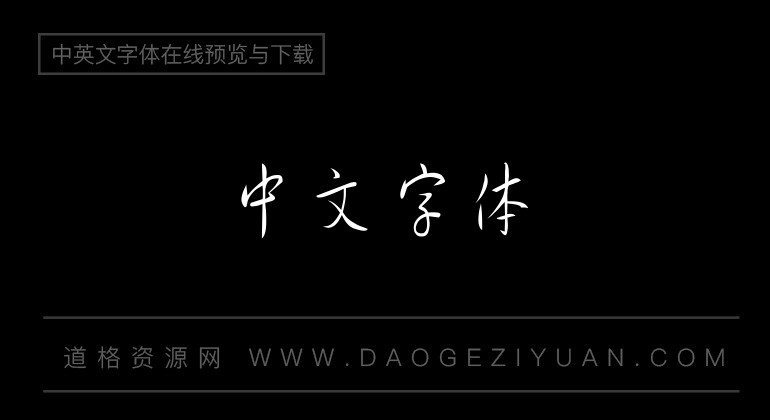
? 金梅细行书字国际码字体是一款经典的中文字体,由知名设计师梅兰竹所设计,它特别适合用于印刷品、报纸和书籍的排版。这款字体的特点是笔画清晰,细腻,符号和汉字之间的间距也很合理,比较节省空间,印刷出来的效果也很漂亮。金梅细行书字国际码字体能够在各种文本编辑器中使用,并且它的支持度也比较高,可以在多种操作系统中使用。文件名:JinMeiXiXingShuZiGuoJiMa-1.ttf
金梅细行书字国际码是一款非常不错的手写艺术字体,具有很好的视觉感,适合于文化类的宣传设计、商业类品牌的广告和产品包装设计以及个性化文字排版等较多场景。